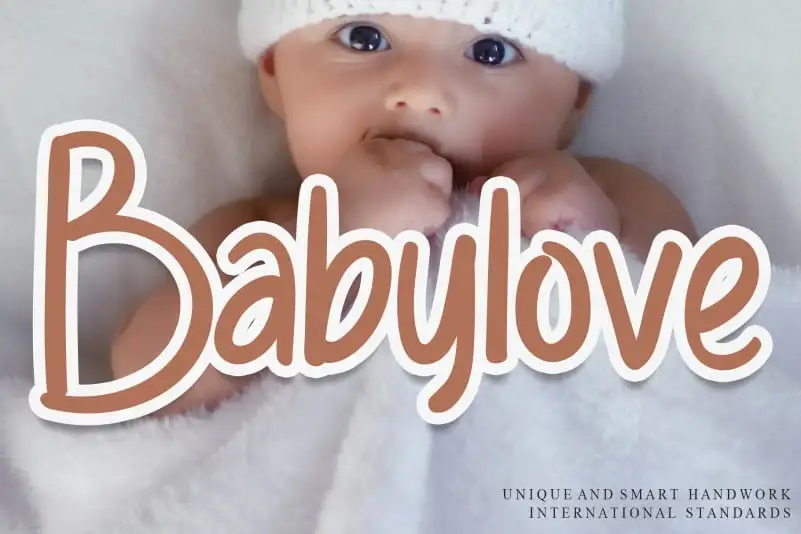
Babylove Display Font – Download Grátis
Nossa fonte ‘Babylove Display Font’ é perfeita para quem busca um charme especial em suas criações digitais. Desenvolvida pela criativa equipe do designer creativeletter, esta fonte vem rica em detalhes e personalização única. Ela oferece uma experiência de escritura que vai além da tecnologia comum, tornando-a a escolha ideal para artistas gráficos buscando um toque especial em seus trabalhos. Seja você um mestre do design ou apenas iniciante, esta fonte não só facilitará sua expressão artística, mas também permitirá que seu trabalho brilhe mais. Engajue-se com Babylove Display Font e deixe-nos mostrar como ela pode revolucionar a maneira como você se expressa em seu próximo projeto visual.